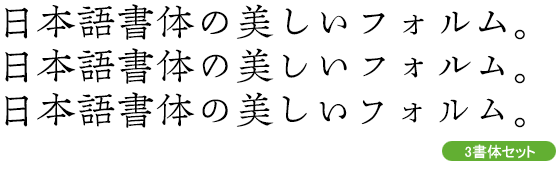
アンチック体
中世安竹体 方広M Combination 3
KOKotonohaHoko-M, KOTamayuraHoko-M, KOMinamotoHoko-M
和字アンチック体「ことのはM」「たまゆらM」「みなもとM」それぞれに、漢字書体「方広M」と欧字書体「K.E.Pisces Medium」を組み合わせた3書体(「KOことのは方広M」「KOたまゆら方広M」「KOみなもと方広M」)の3書体セットです。
日本と中国、欧米の古い書物などから復刻した和字書体(かなとカナ)と漢字書体、欧字書体を組み合わせ、伝統に基づいた新たな活字書体を制作しています。